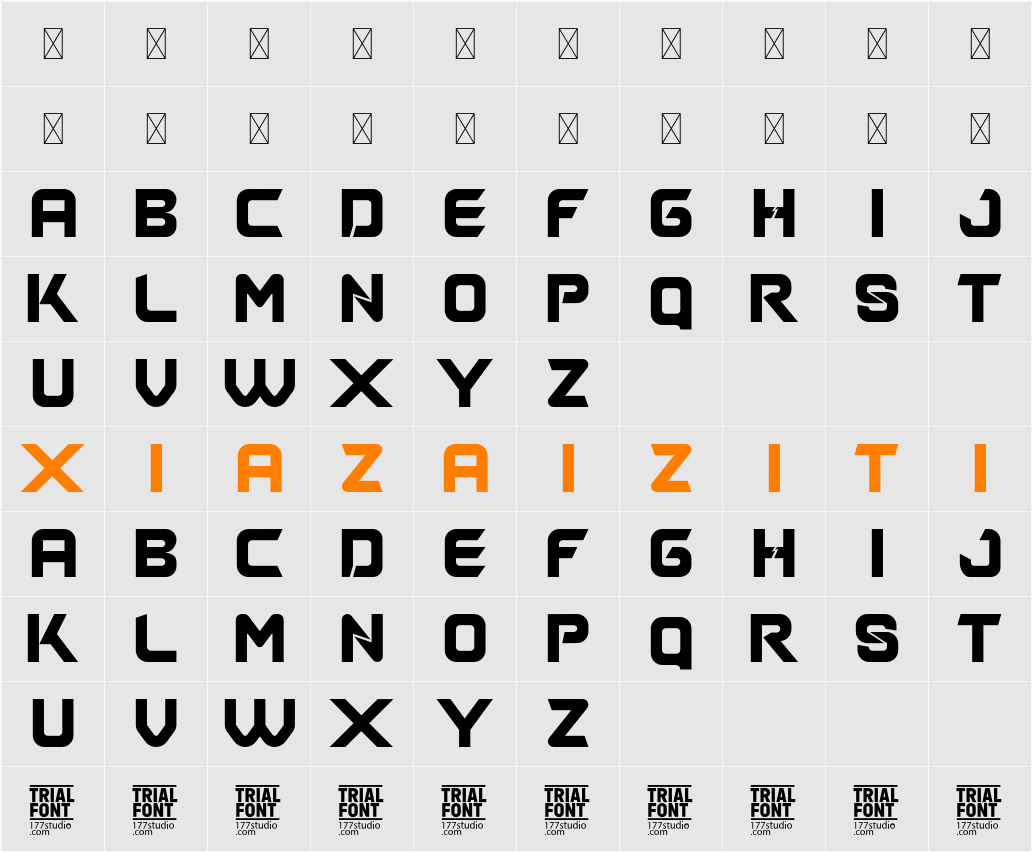
Revered Through Demo
Revered Through Demo,这款字体结构工整、笔画清晰,兼顾美观与易读性,适用于标题、正文、海报、包装、LOGO 等多种场景。字形优雅稳定,风格百搭耐看,适配日常排版与创意设计,让文字呈现更舒适、更具质感。Revered Through Demo一笔一画,皆是细节,以均衡的比例、流畅的线条打造舒适视觉体验,字形端正大气,风格简约现代。无论是商业设计、品牌宣传还是日常排版,都能轻松驾驭,让文字更有格调与力量。Revered Through Demo字体下载。
• 字体名称: Revered Through Demo